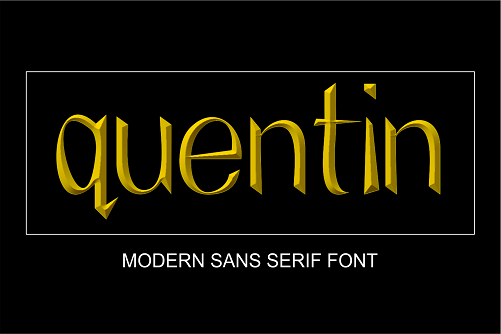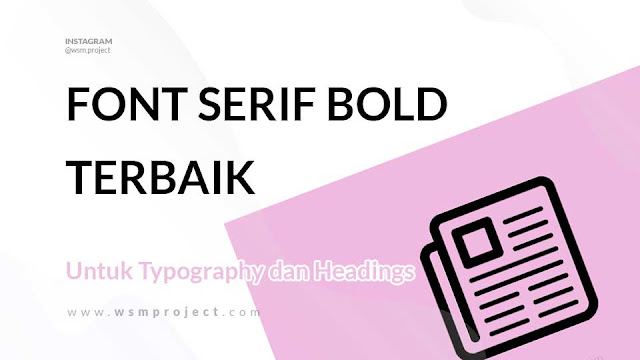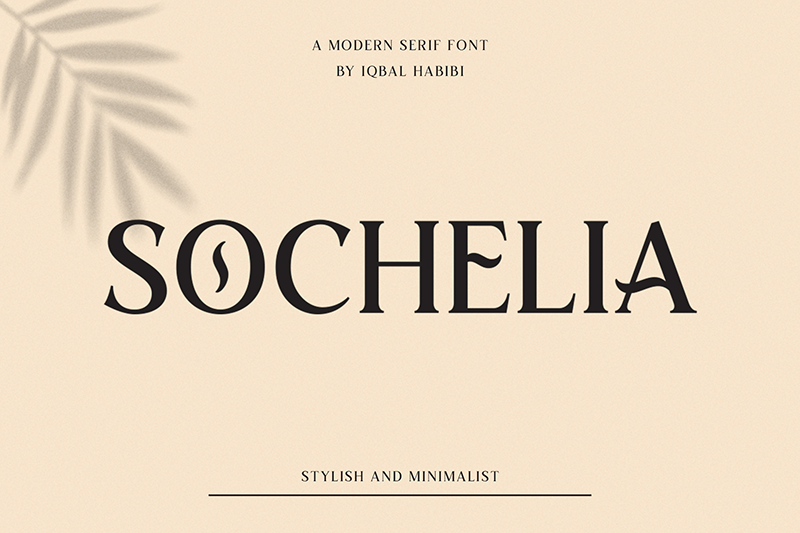
Campuran antara garis tebal dan tipis membuat set simbol yang bagus violina typeface.
Font serif yang bagus. Kira kira kan dengan kebutuhannya jika cocok ya dipakai kalau kurang pas ya dicoba dengan font sans serif yang lainnya. Jadi jika anda tidak ingin resume anda terlihat seperti ratusan resume yang lain anda pasti akan memilih jenis font yang lain. Sangat banyak sekali jenis font tipografi itu ada sans serif serif display handwriting dan masih banyak lagi. Serif yang terinspirasi fashion ini adalah tambahan fantastis pada koleksi font yang berfokus pada pembuatan header kreatif atau desain cetak.
Font pilihan terbaik untuk desain grafis gratispada artikel kali ini saya akan mengupdate tentang font font terbaik dan gratis untuk anda. 30 font sans serif terbaik untuk heading website dalam web desain font berperan sangat penting karena meskipun desain web anda sudah elegan tapi tidak di padu dengan font yang sesuai akan menjadikan web terlihat buruk. Jenis font serif terkenal dengan tampilannya yang memiliki kesan profesional tegas dan elegan. 5 font serif terbaik.
Dan garamond adalah alternatif yang bagus. Selain menyediakan font cantik dengan filter dan contoh font yang baik direktori google web fonts juga menyediakan kombinasi font populer sesuai font yang anda sukai. Tak hanya sekedar bagus saja melainkan keselarasan antara warna penempatan bentuk dan ukuran yang sesuai. Font sans serif terbaik bagus untuk desain.
Bagi siapa saja yang mencintai dunia desain pasti mereka juga berburu font font dalam membangun desain. Font sans serif ini berukuran besar pada garis dan outlinenya serta memiliki sedikit nuansa tulisan tangan. Sebelumnya kamu harus tahu ya perbedaan antara berbagai jenis font tipografi yang ada. Kadang kadang desain web yang sederhana dan bersih akan terlihat menarik dilihat karena penggunaan font yang pas dan menarik.
Meski demikian tidak semua font serif memiliki karakteristik tersebut. Bagus tidaknya font sans serif yang sudah saya sebutkan dan rekomendasikan kepada bro sis diatas kembali lagi kepada selera masing masing. Tentunya yang jelas adalah sesuaikanlah dengan kebutuhan bro sis saat ini. Beberapa contoh font serif yang tak asing diantaranya adalah times new roman dan palatinofont serif memiliki ciri adanya lengkung atau kait di bagian atas huruf dan semacam alas kaki di bagian bawah.
Kliennya tidak memilih logo ini dan liz tidak ingin menyia nyiakan font yang begitu bagus jadi font ini diunggah di behance supaya dapat diunduh gratis. Jenis huruf serif sepanjang masa seperti times new roman pendahulu garamond sudah digunakan selama 500 tahun. Ada banyak sekali jenis font keren di internet yang dapat digunakan secara gratis oleh desainer grafis namun tetap harus memperhatikan proporsi dan perpaduannya dengan warna dan gambar.